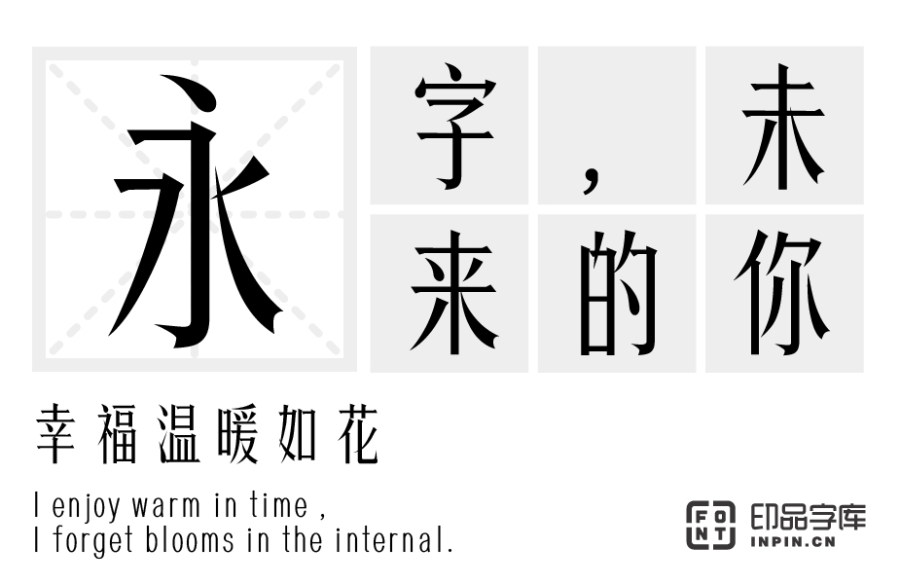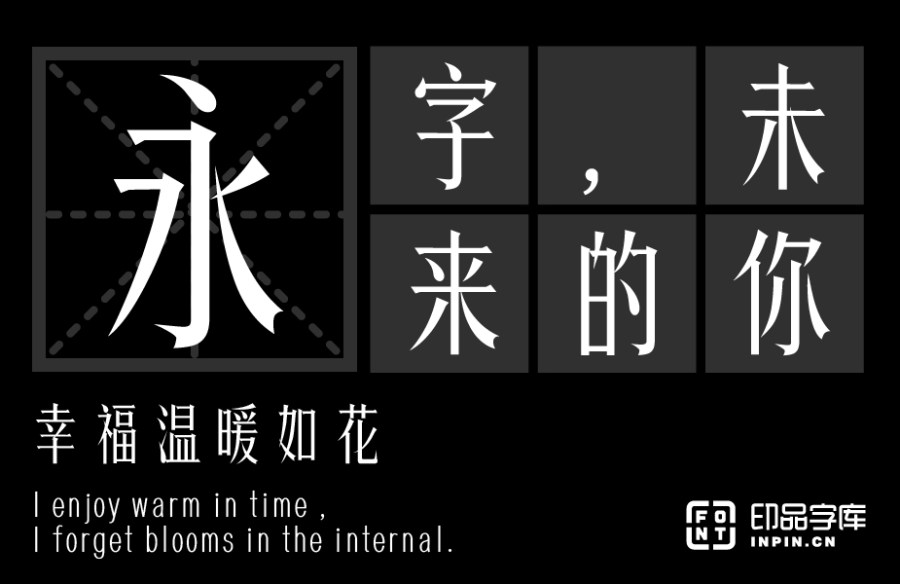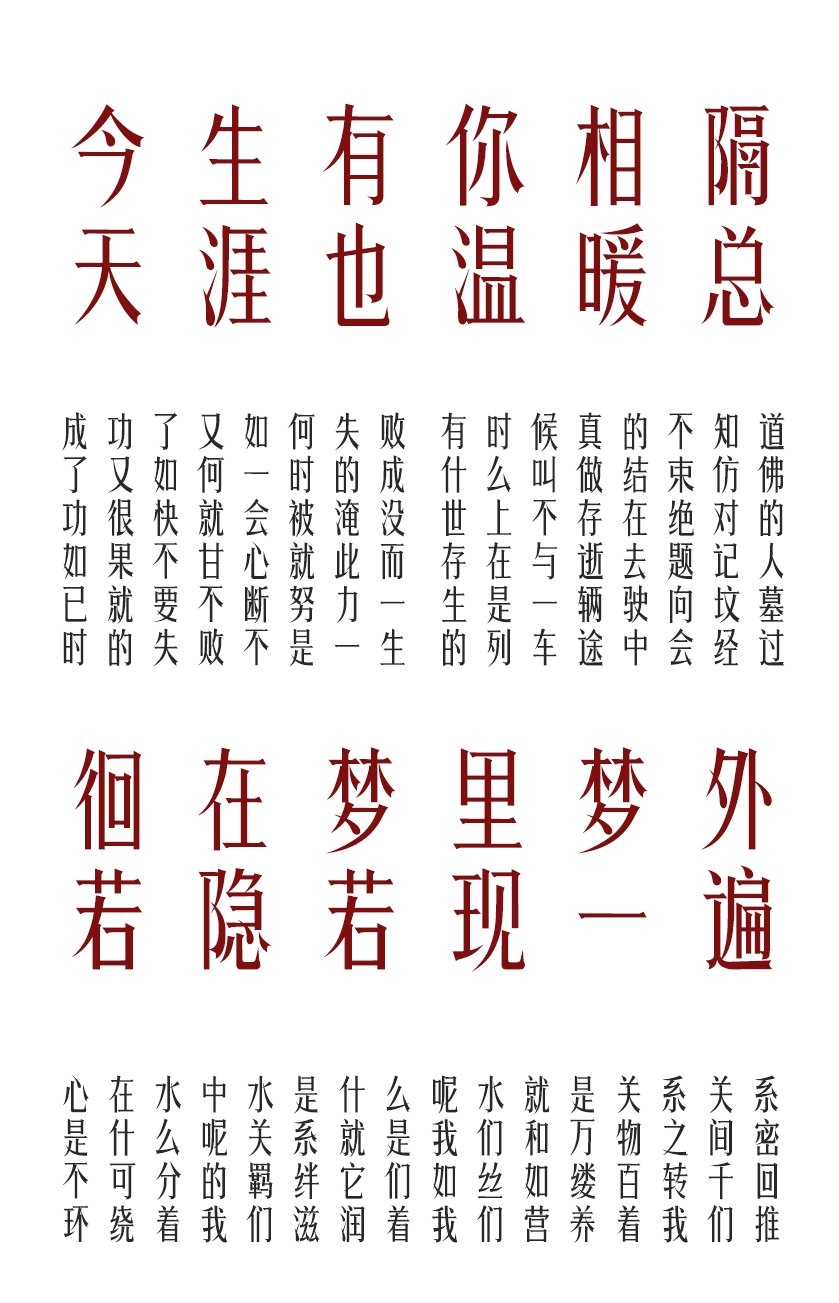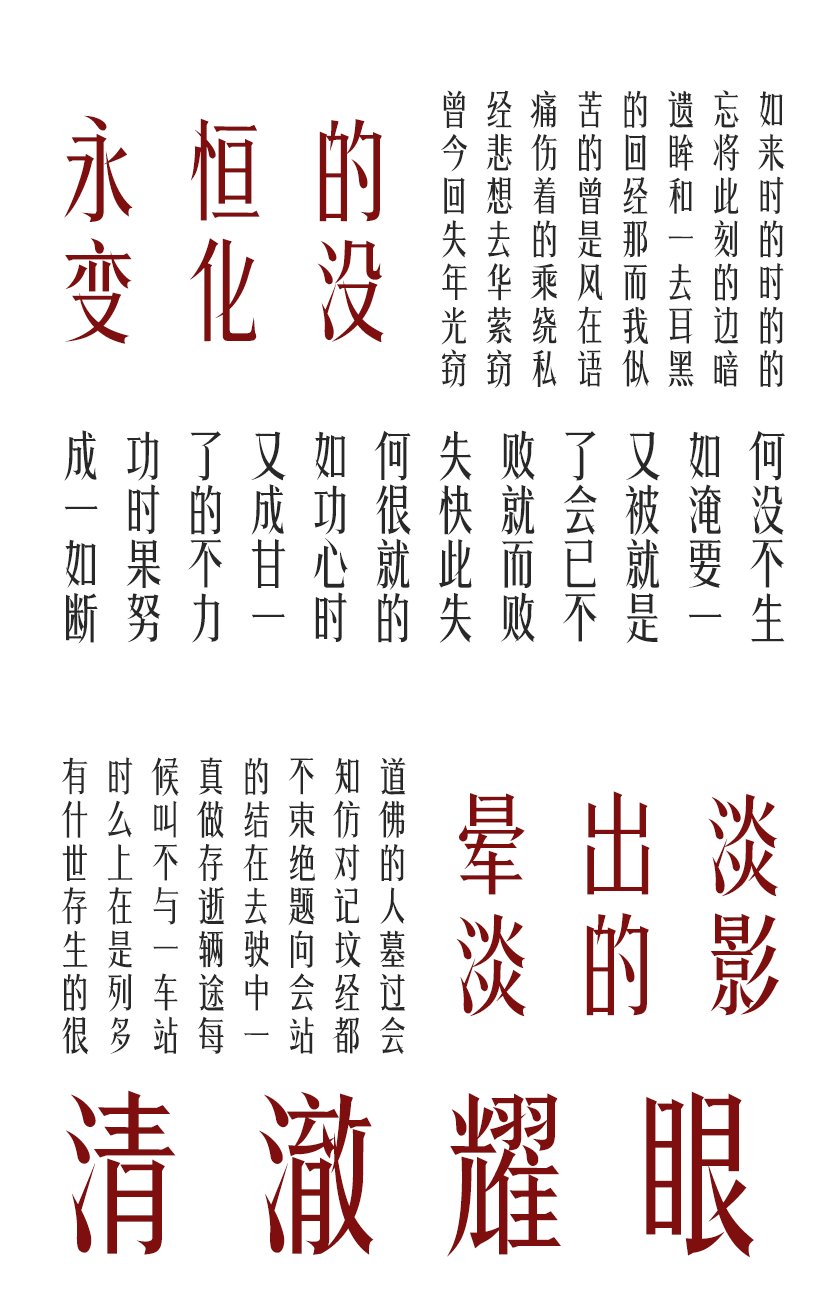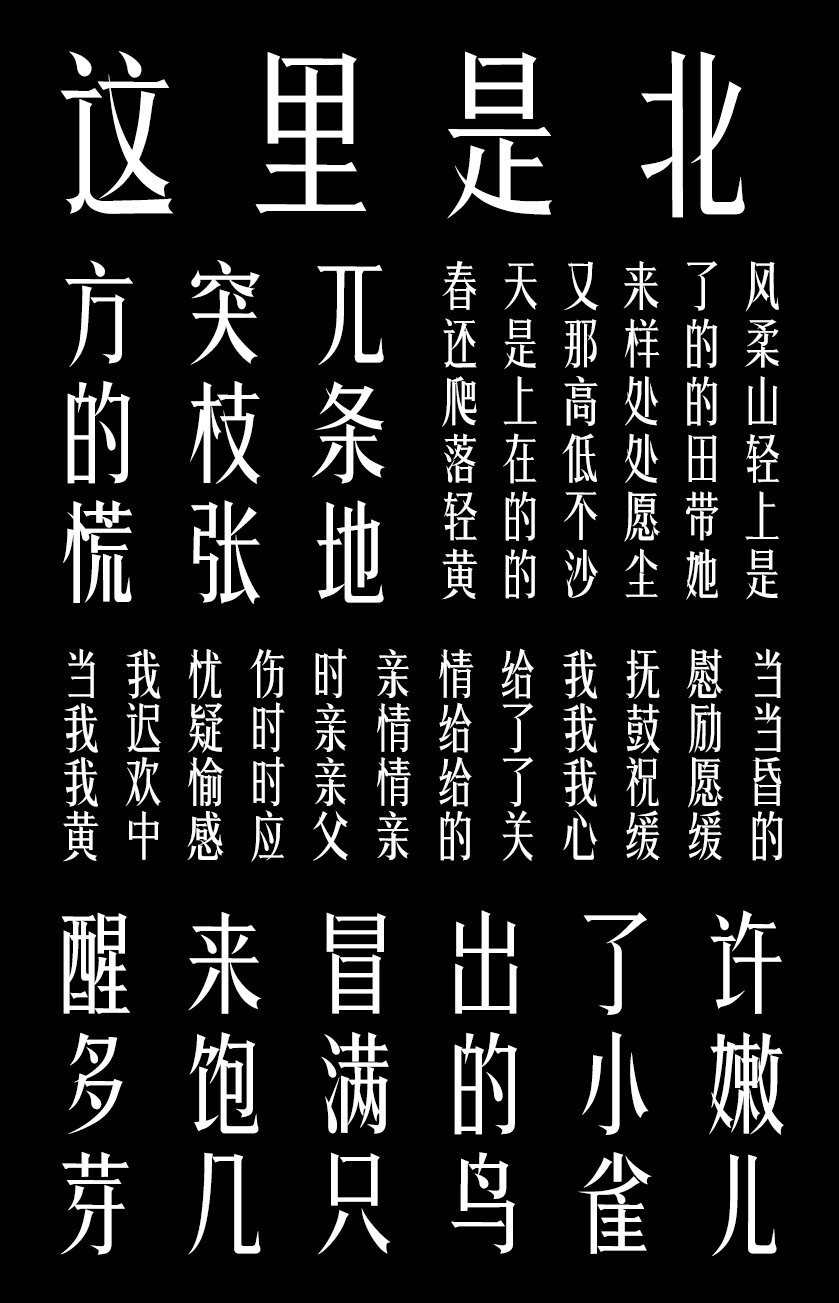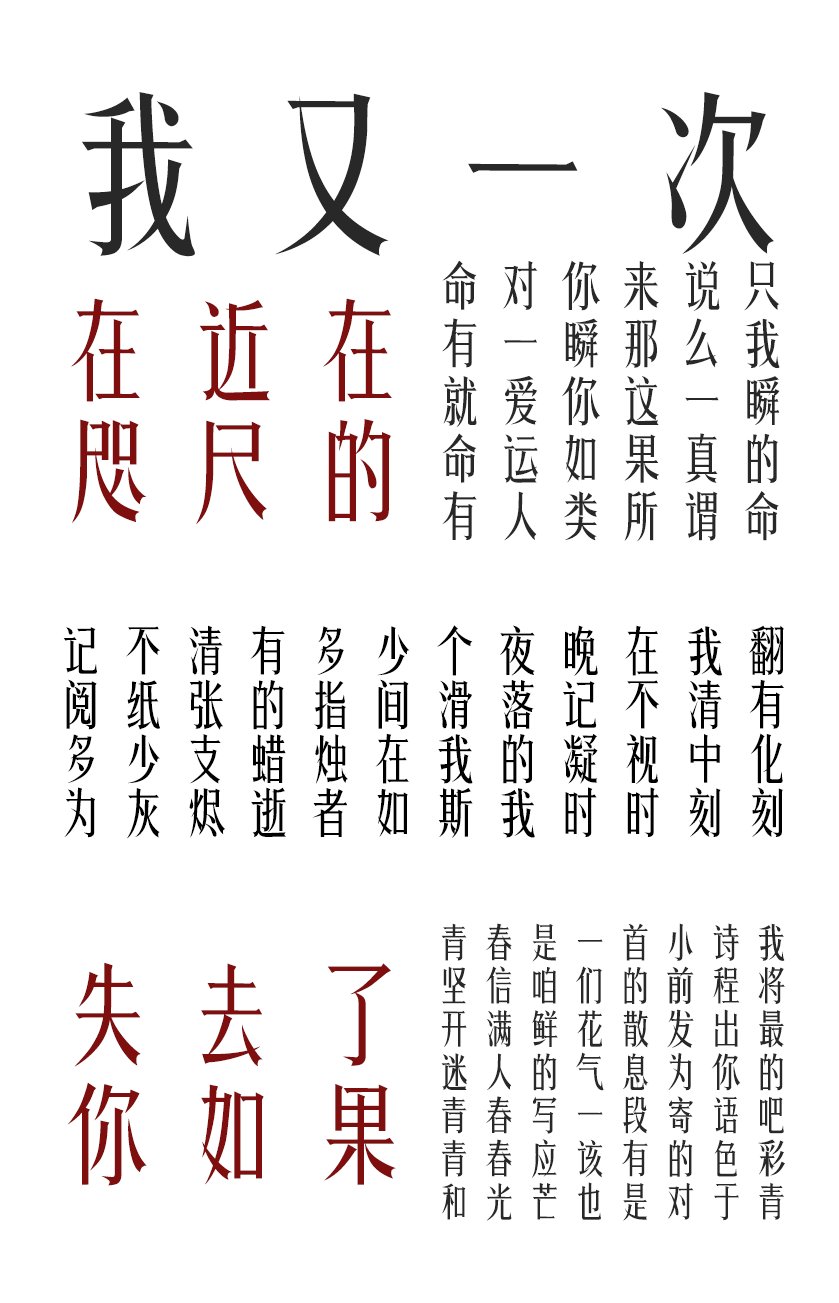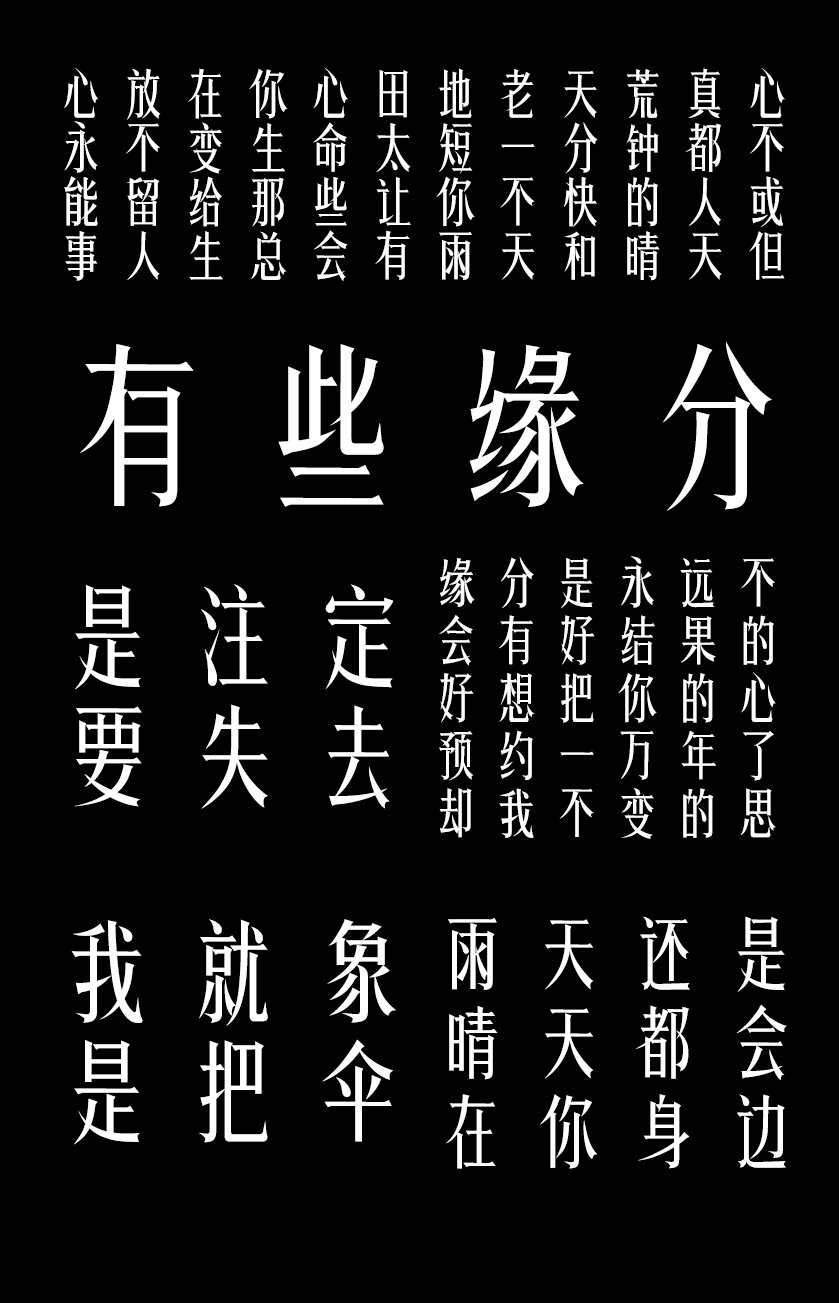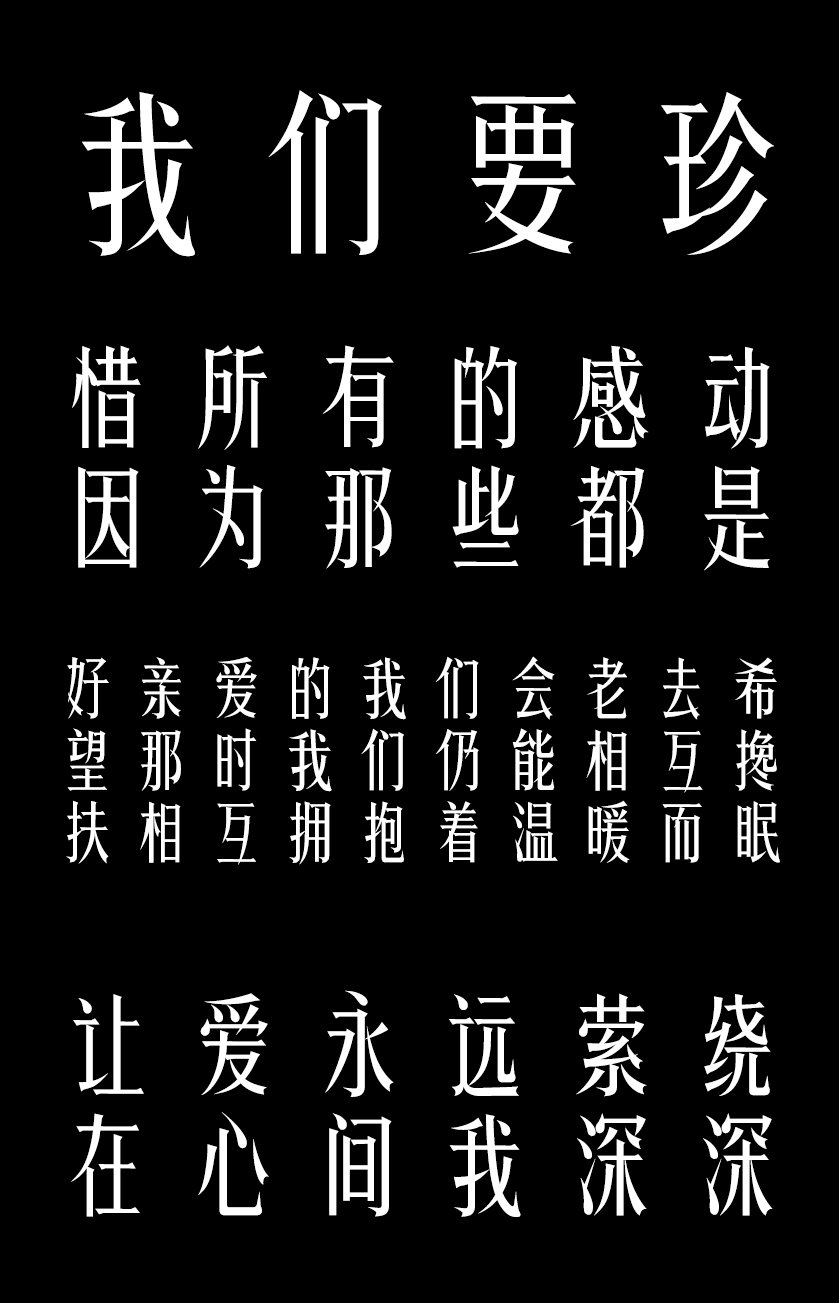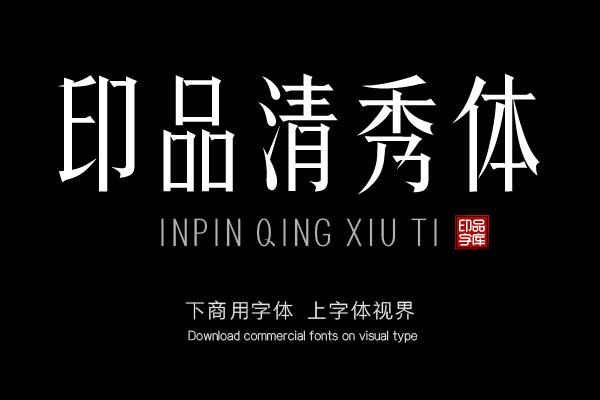
印品清秀体
印品清秀体,一款气质娟秀,清雅悦目,个性鲜明的字体,字形工整秀长,细节飘逸。笔画更加纤细修长,整体看起来舒服易读,适用于带有清和雅致风格的标题和正文排版。
• 印品清秀体,是一款气质娟秀,清雅悦目,个性鲜明的宋体字体。工整秀长,穿透的尖端。笔画均匀,末端有装饰角,点、撇、捺、钩等笔画有穿透的尖端,使字体更具有识别度。字形工整秀长,细节飘逸。这款字简洁明快,笔画更加纤细修长,整体看起来舒服易读,适用于带有清和雅致风格的标题和正文排版,与黑体一样是经典。